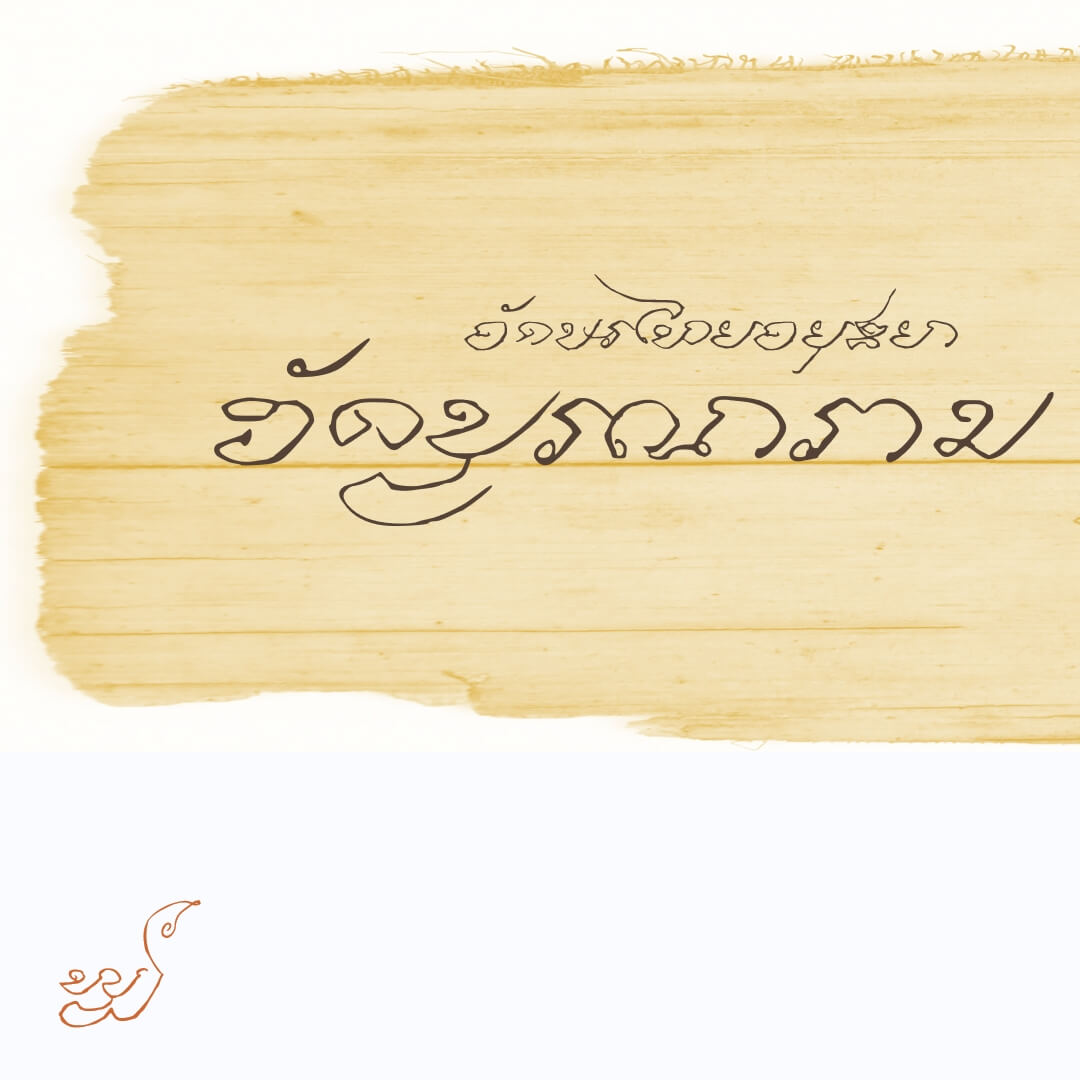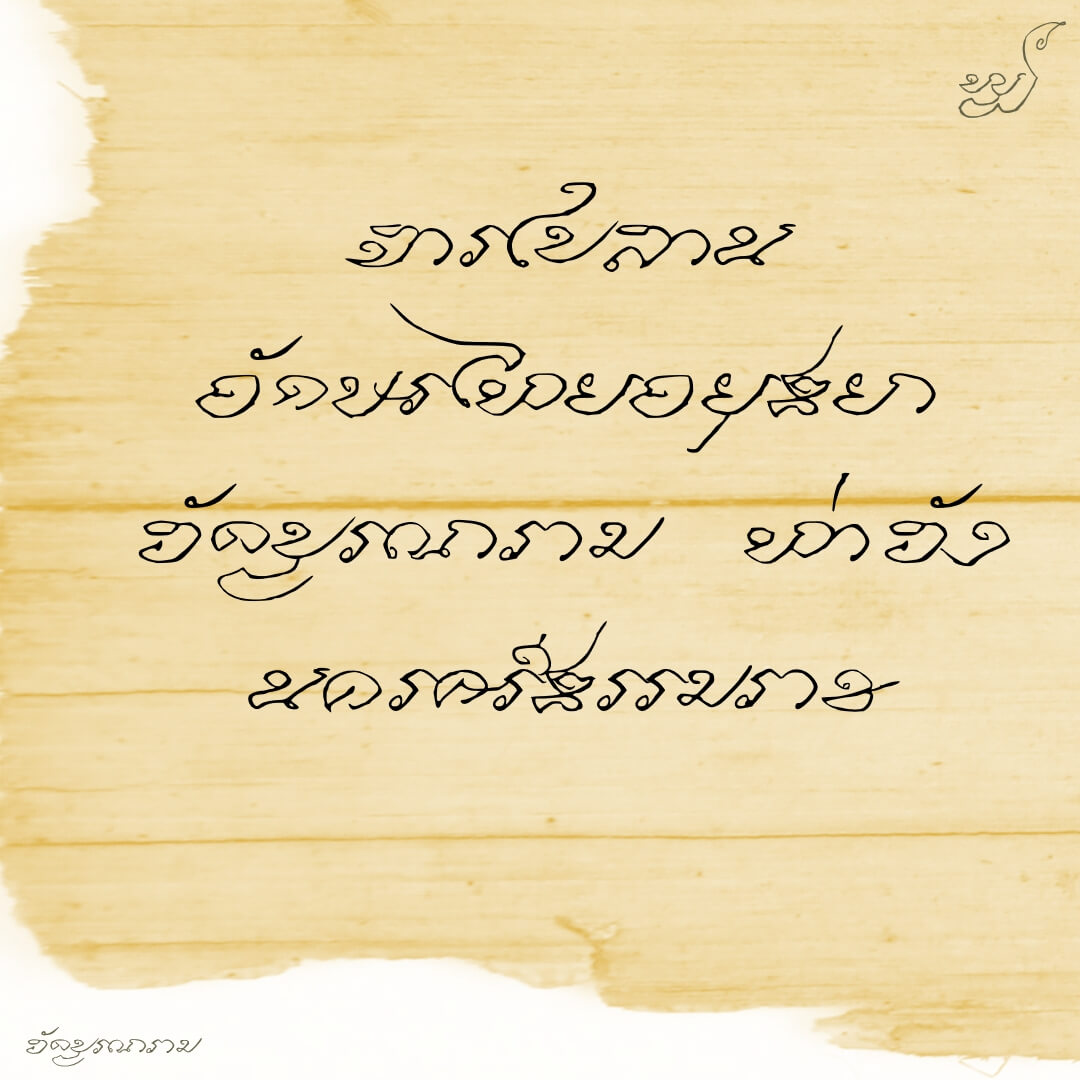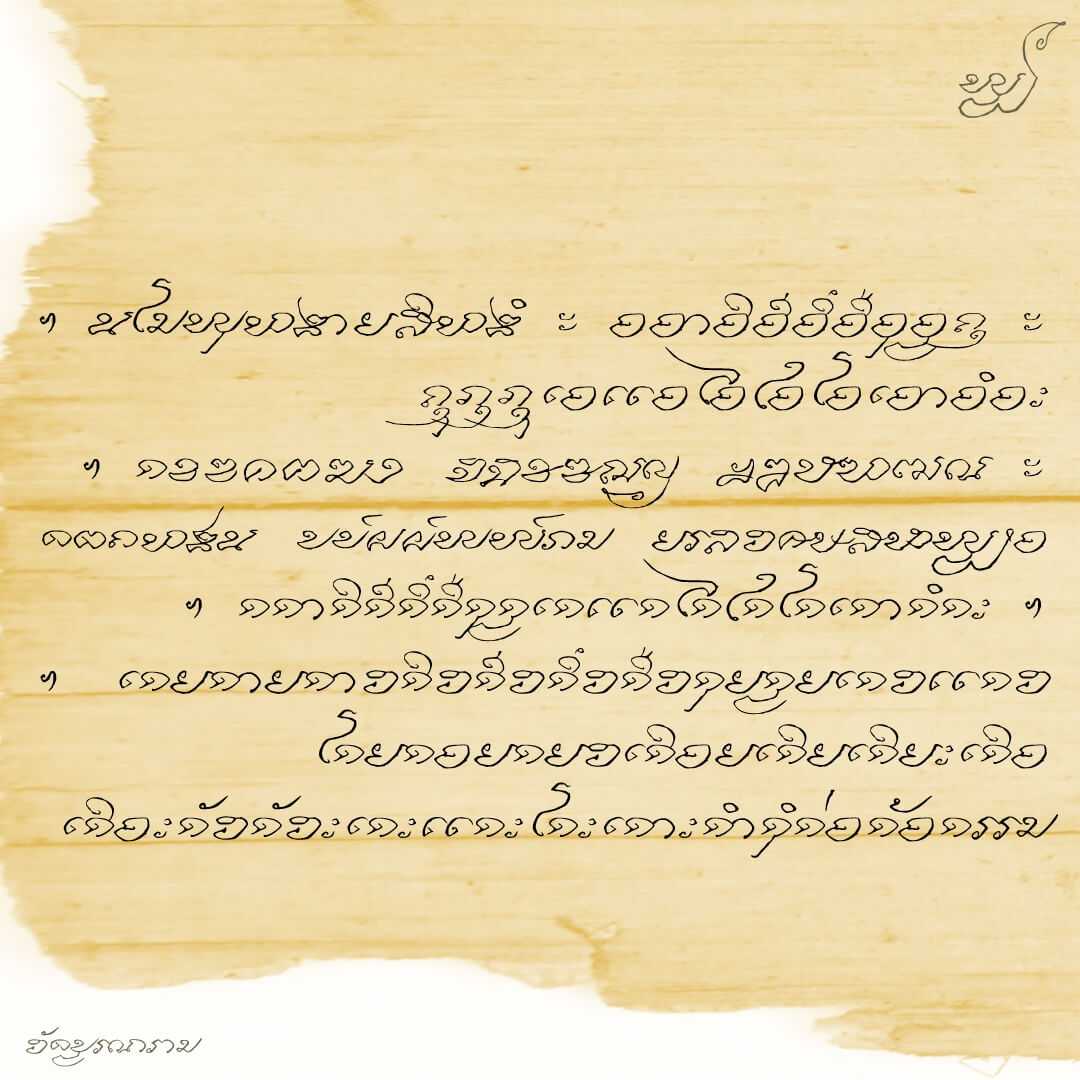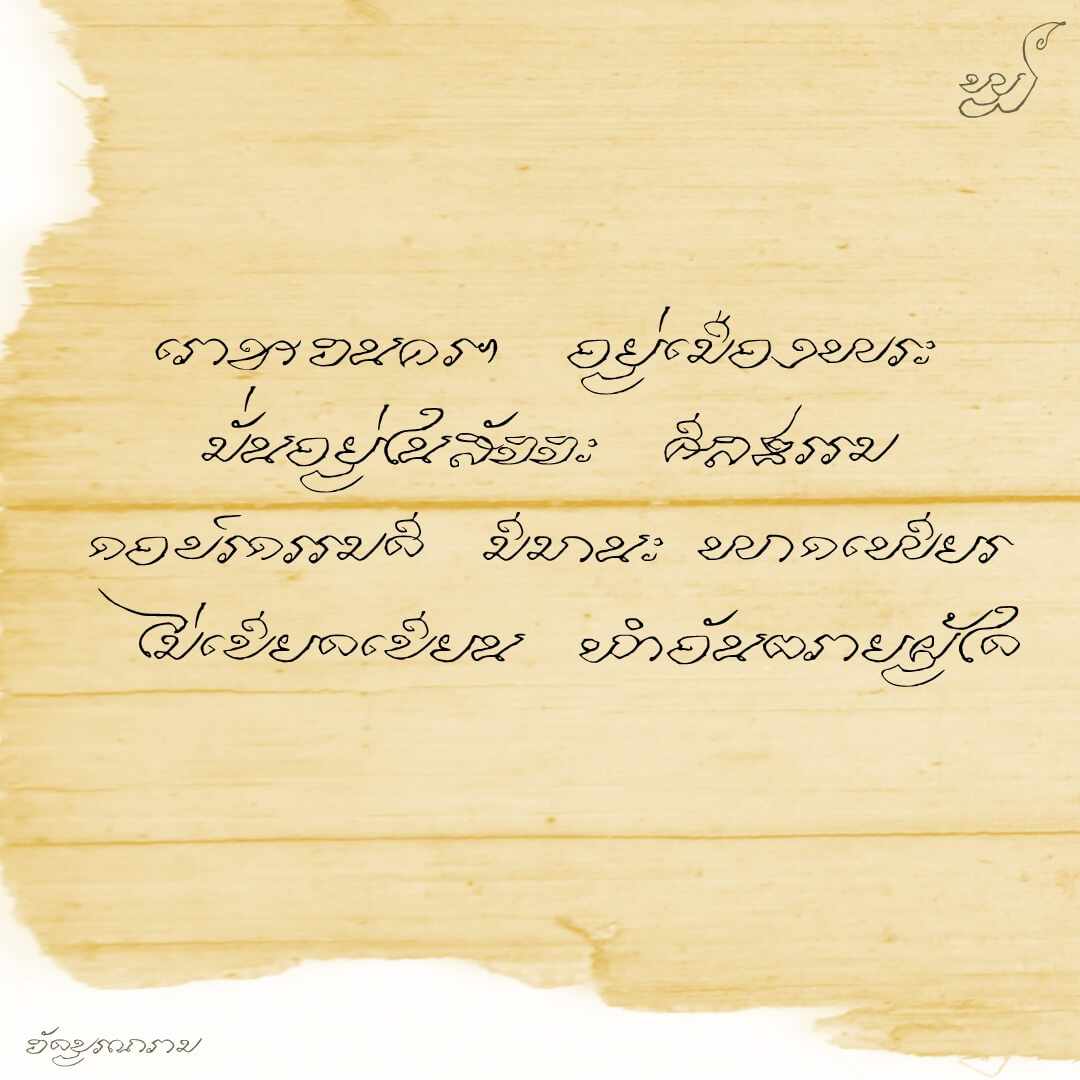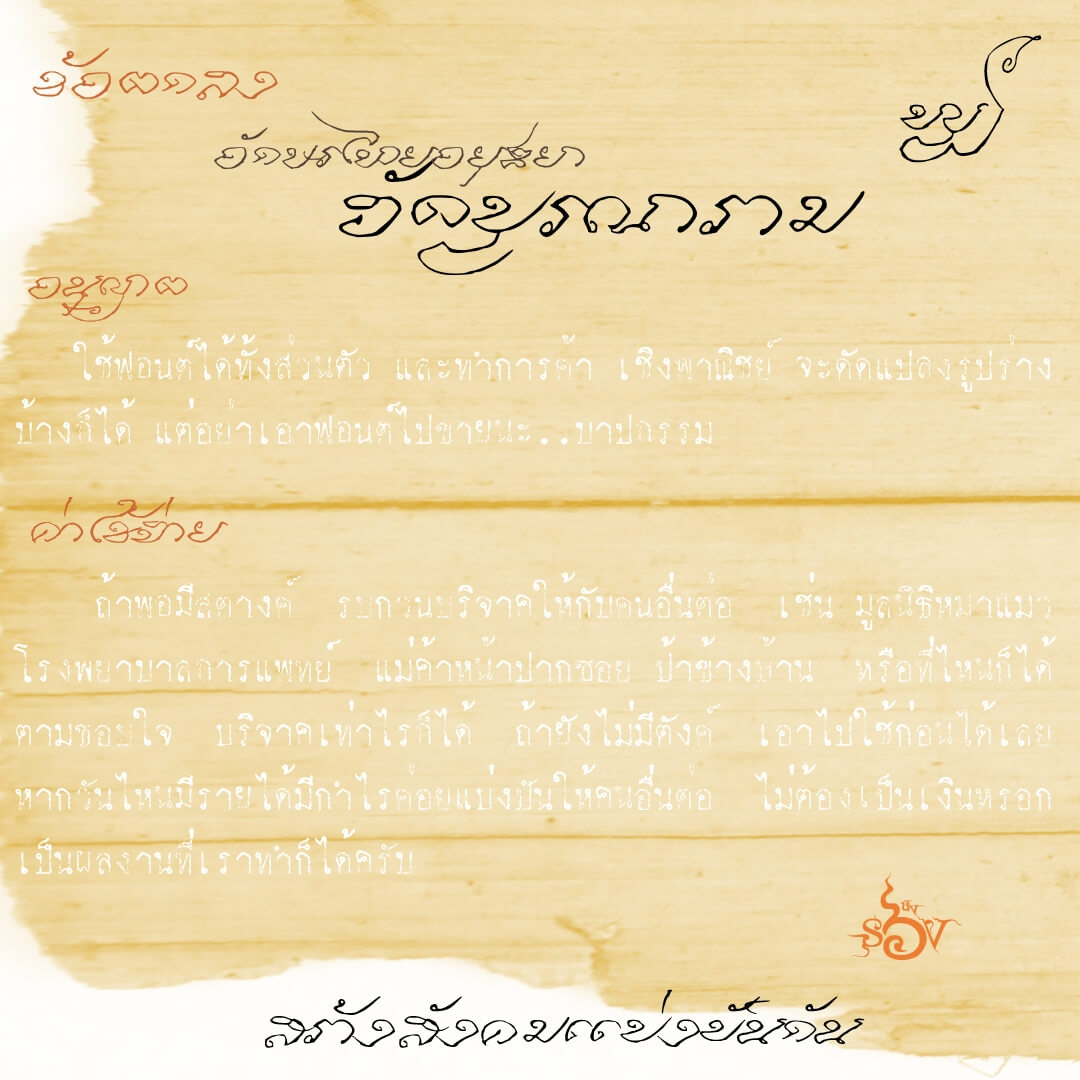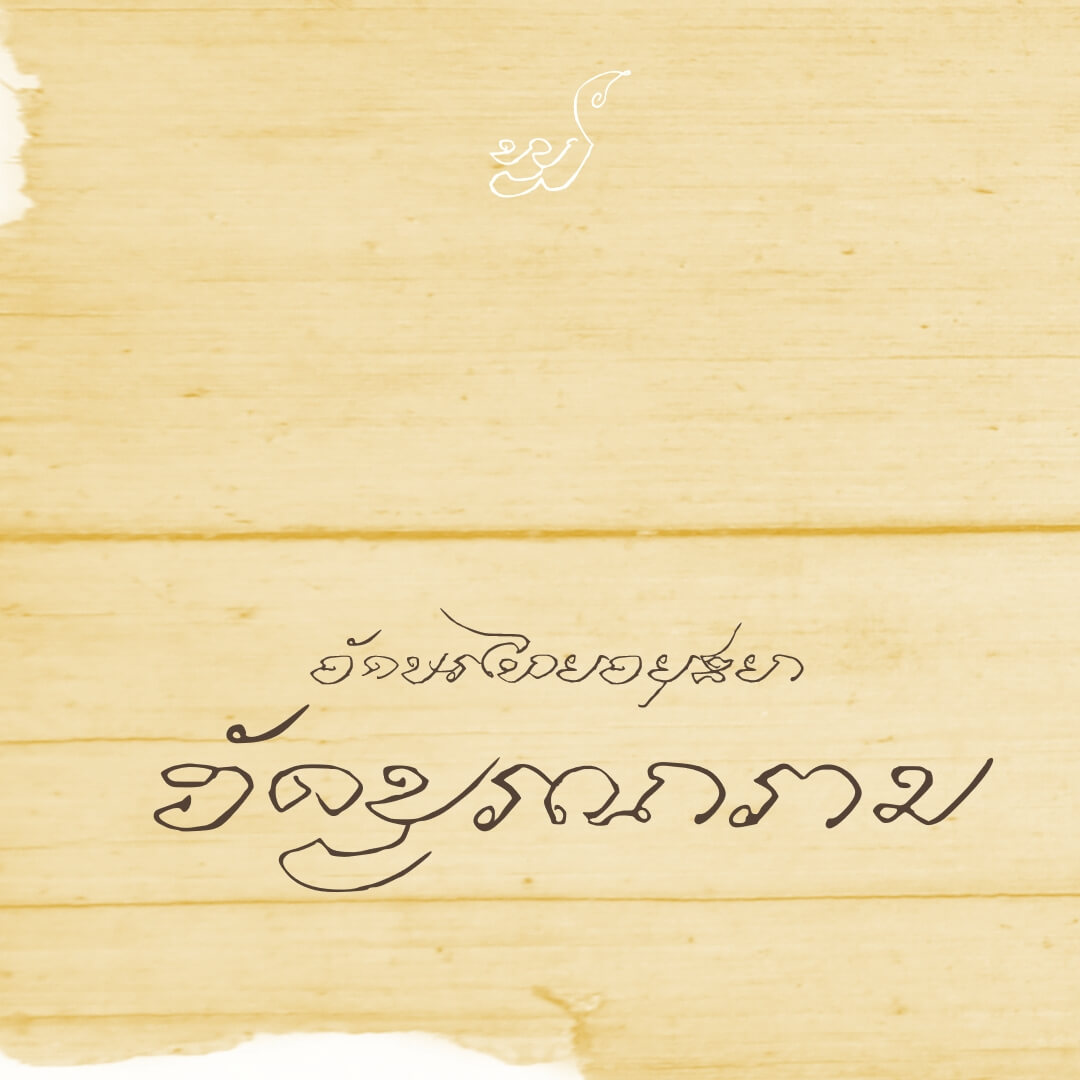
ฟอนต์วัดบูรณาราม – ฟอนต์นี้ต้นทางมาจาก ใบลาน วัดบูรณาราม สี่แยกท่าวัง อ.เมือง จ.นครศรีธรรมราช เป็นอักษรไทยสมัยอยุธยา (ส่วนช่วงเวลาใดไม่ปรากฏในเอกสาร ต้องลองพิจารณาศึกษาเพิ่มเติมกันเอาเอง)
รอบนี้ใช้วิธีการ convert จากรูปถ่ายการจารอักษรบนในลาน มาเป็น vector ตรงๆ เนื่องจากมีตัวอักษรค่อนข้างครบถ้วน (แต่ก็แอบมีปรับแก้บ้างบางตัวอักษร กับการเข้าคู่สระ)
เบื้องหลังการออกแบบ : ฟอนต์ วัดบูรณาราม